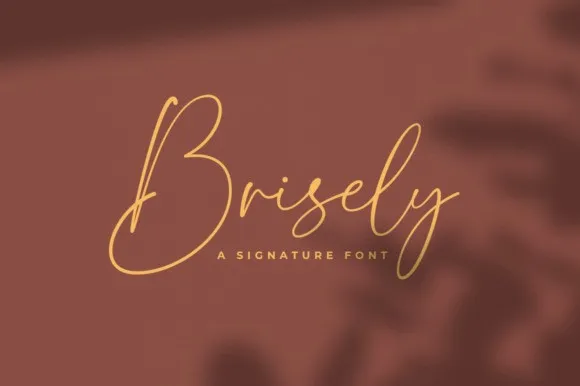
Aqui está uma versão dos dois parágrafos curtos no português para a página de download da font ‘Brisely Signature Font’: Introduzimos uma fonte puramente escrita à mão, com características naturais e um estilo elegante. A Brisely é uma fonte escrita à mão que oferece um design sofisticado e autêntico, capaz de dar a seus projetos uma sensação única e genuína. Perfeita para estilos modernos como marca pessoal, convites de casamento e até mesmo designs de aniversário, ela é perfeita para quem busca um toque cuidadosamente elaborado em seus trabalhos. É simplesmente inegável a beleza natural desta fonte e sua qualidade superior, o que torna uma opção perfeita para designers em qualquer fase do processo criativo.